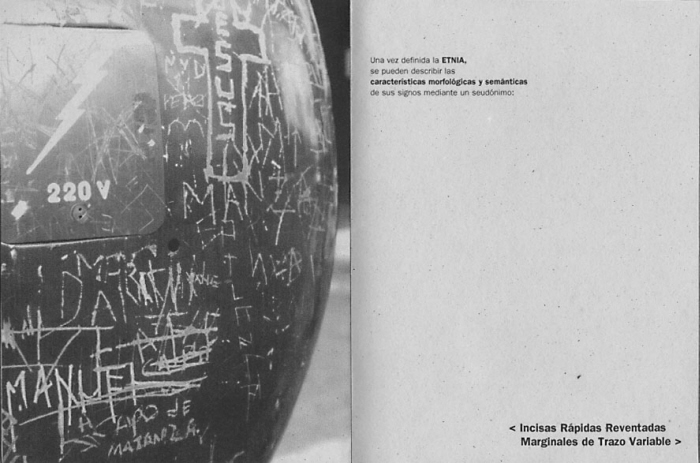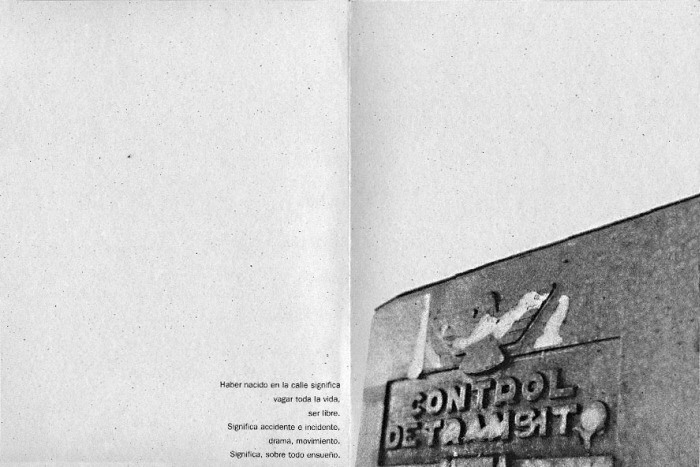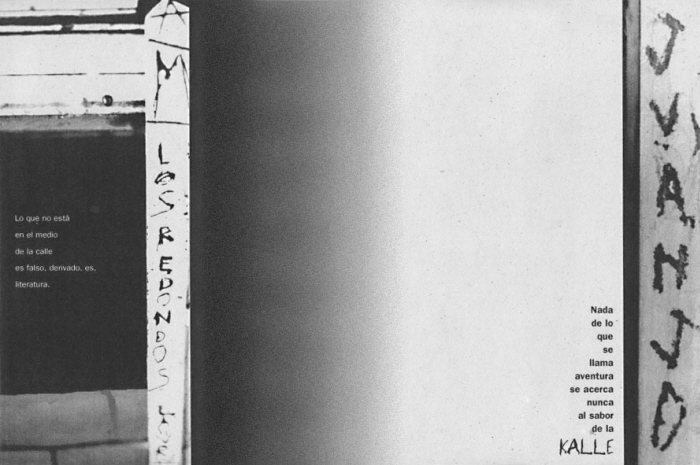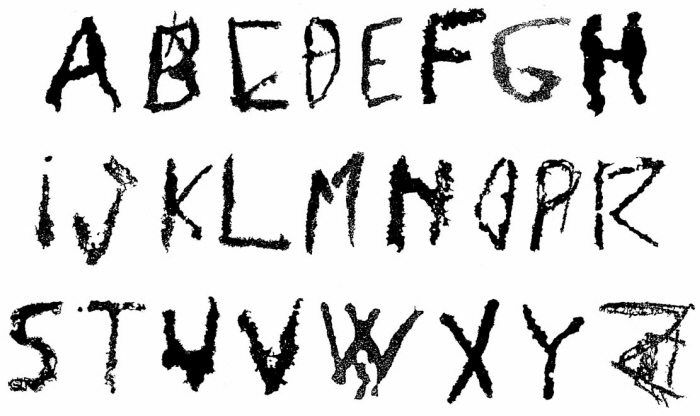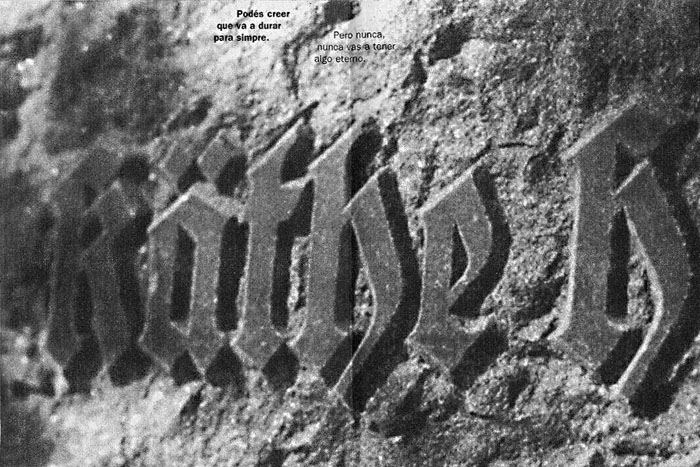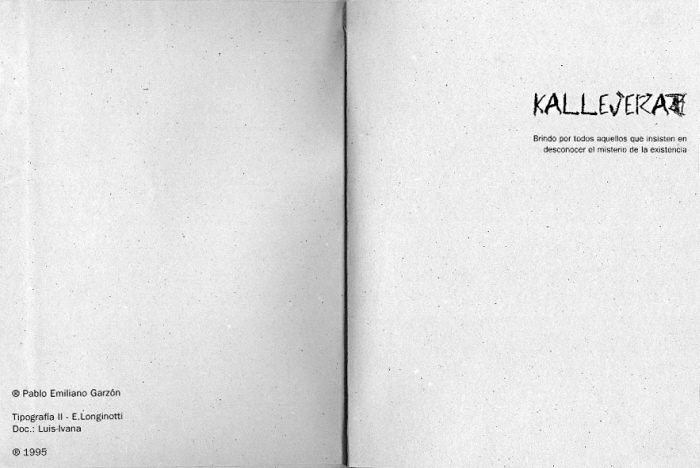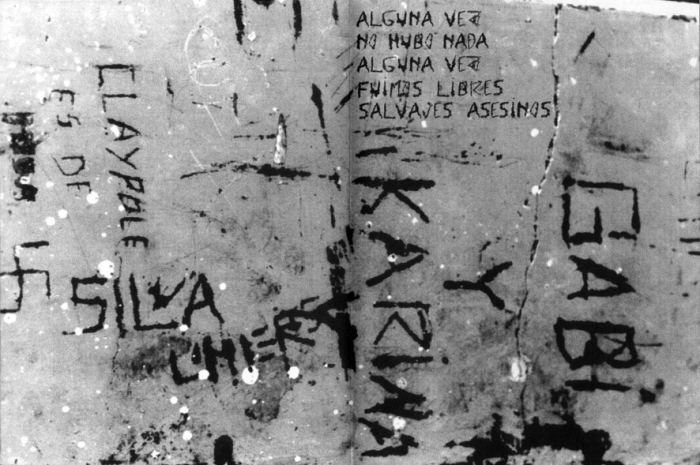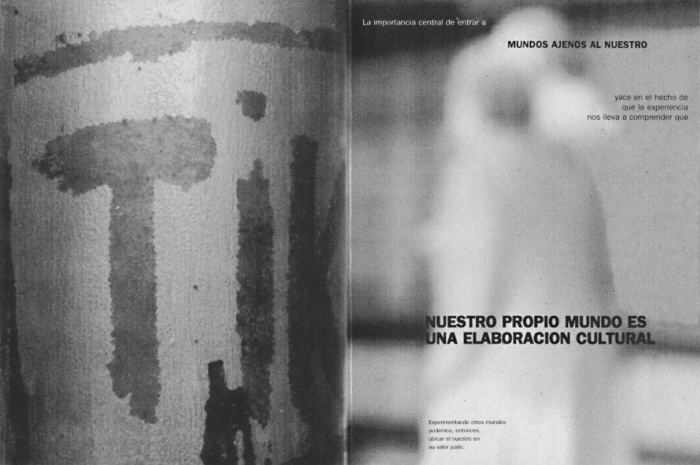
Cover - Generacion de una tribu tipografica a partir de fotografias de inscripciones de letras, cuyas caracteristicas morfologicas son: 'incisas rapidas reventadas marginales de trazo variable'. 1995
Spread 2-3 - Generacion de una tribu tipografica a partir de fotografias de inscripciones, cuyas caracteristicas morfologicas son: 'incisas rapidas reventadas marginales de trazo variable'.
Spread 4-5 - Haber nacido en la calle significa vagar toda la vida, ser libre. Significa accidente e incidente, drama, movimiento. Significa, sobre todo ensueño.
Spread 6-7 - Generacion de una tribu tipografica a partir de fotografias de inscripciones, cuyas caracteristicas morfologicas son: 'incisas rapidas reventadas marginales de trazo variable'.
Spread 8-9 - Generacion de una tribu tipografica a partir de fotografias de inscripciones, cuyas caracteristicas morfologicas son: 'incisas rapidas reventadas marginales de trazo variable'.
Spread 10-11 - Generacion de una tribu tipografica a partir de fotografias de inscripciones, cuyas caracteristicas morfologicas son: 'incisas rapidas reventadas marginales de trazo variable'.
Spread 12-13 - Generacion de una tribu tipografica a partir de fotografias de inscripciones, cuyas caracteristicas morfologicas son: 'incisas rapidas reventadas marginales de trazo variable'.
libres salvajes asesinos - Generacion de una tribu tipografica a partir de fotografias de inscripciones, cuyas caracteristicas morfologicas son: 'incisas rapidas reventadas marginales de trazo variable'.
abc...tribu - Generacion de una tribu tipografica a partir de fotografias de inscripciones, cuyas caracteristicas morfologicas son: 'incisas rapidas reventadas marginales de trazo variable'.